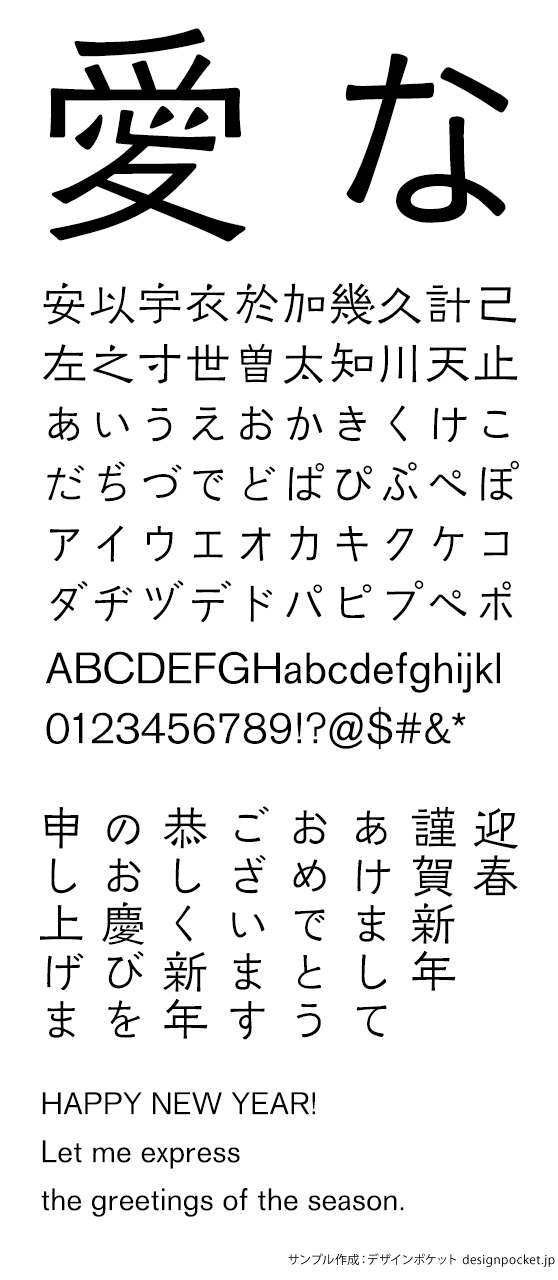
KOくろふね銘石M
KOKurofuneMeiseki-M
『沿溝書体スタイルブック』(草間京平著、日本孔版文化の会、1952)から翻刻した謄写版のゴシック体「くろふね」に、『王興之墓誌』(341)と『王興之妻宋和之墓誌』(348)にもちいられた字様をもとに翻刻した「銘石」、1898年にドイツ・ベルリンのベルトルド活字鋳造所が製作した「アクチデンツ・グロテスク」をベースにした「K.E.Sagittarius」を組み合わせた「KOくろふね銘石B」のファミリーで、メディウム・ウエイトです。
※「銘石M」の漢字は第一水準限定です。
漢字は第一水準限定です。ギリシャ文字、キリル文字、等幅半角字形、罫線、カタカナ合字など含まれていません。